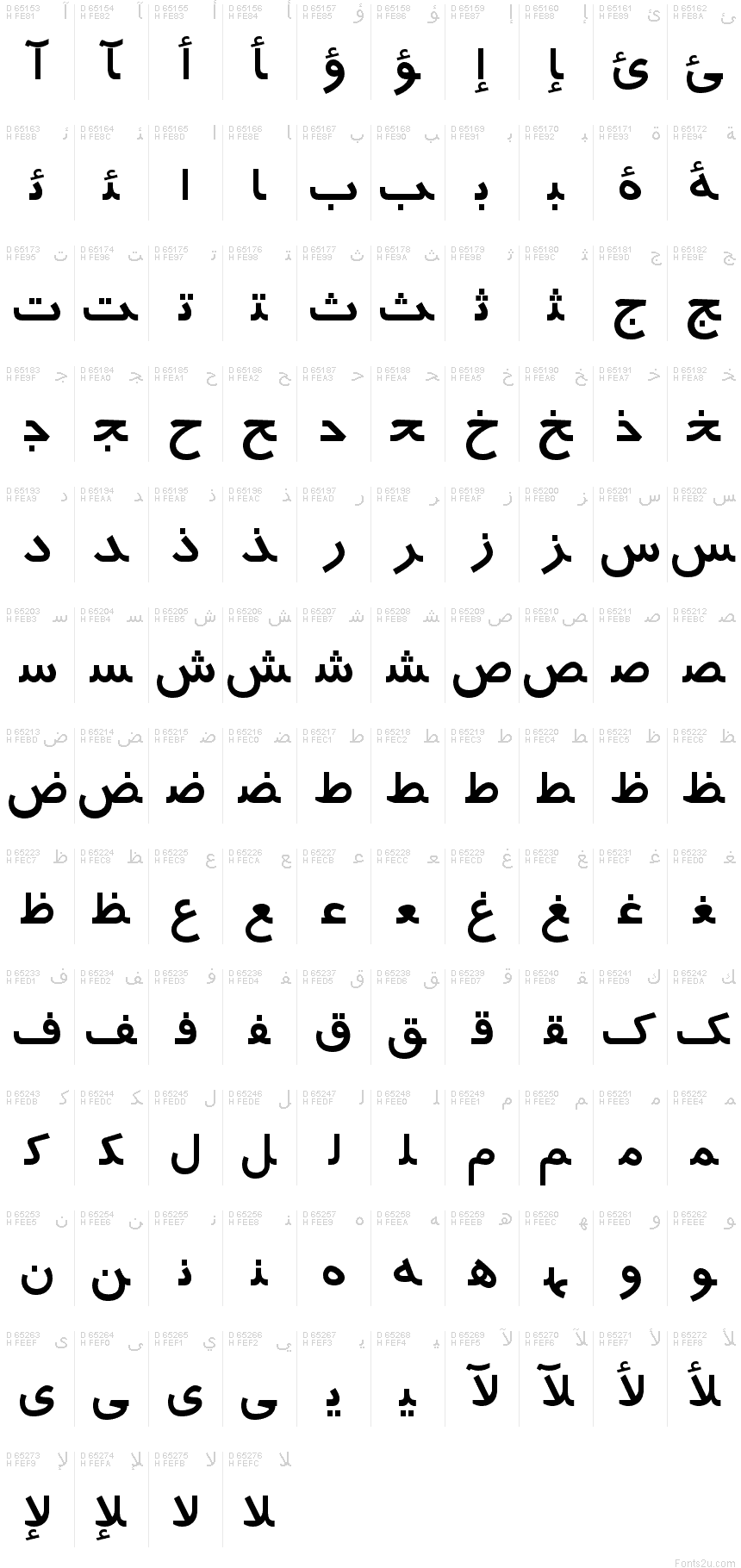
B Traffic Bold, de Borna Rayaneh, é uma fonte display árabe gratuita com o visual de sinalização viária. As letras são compactas e sólidas, com curvas quadradas e um ritmo firme e estruturado que torna o estilo mais funcional do que caligráfico.
Este tom é ideal para gráficos de trânsito, sinalização de fachadas, embalagens, títulos de cartazes e etiquetas de interface, onde você deseja que o letramento árabe pareça direto e urbano. Como é uma fonte gratuita, também é muito útil para títulos, mockups de wayfinding e linhas curtas de branding, especialmente quando uma textura firme e funcional é mais importante que ornamentos.